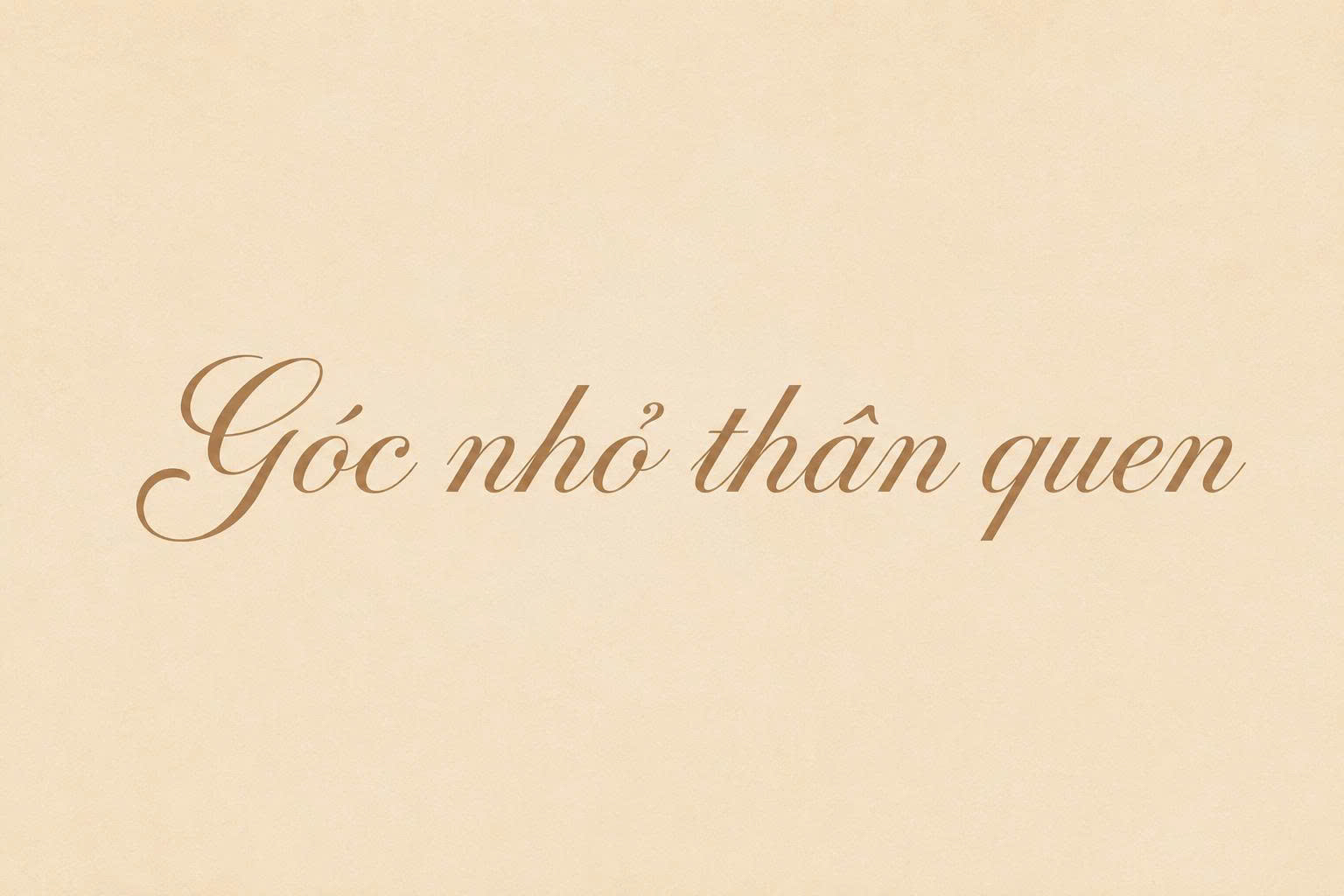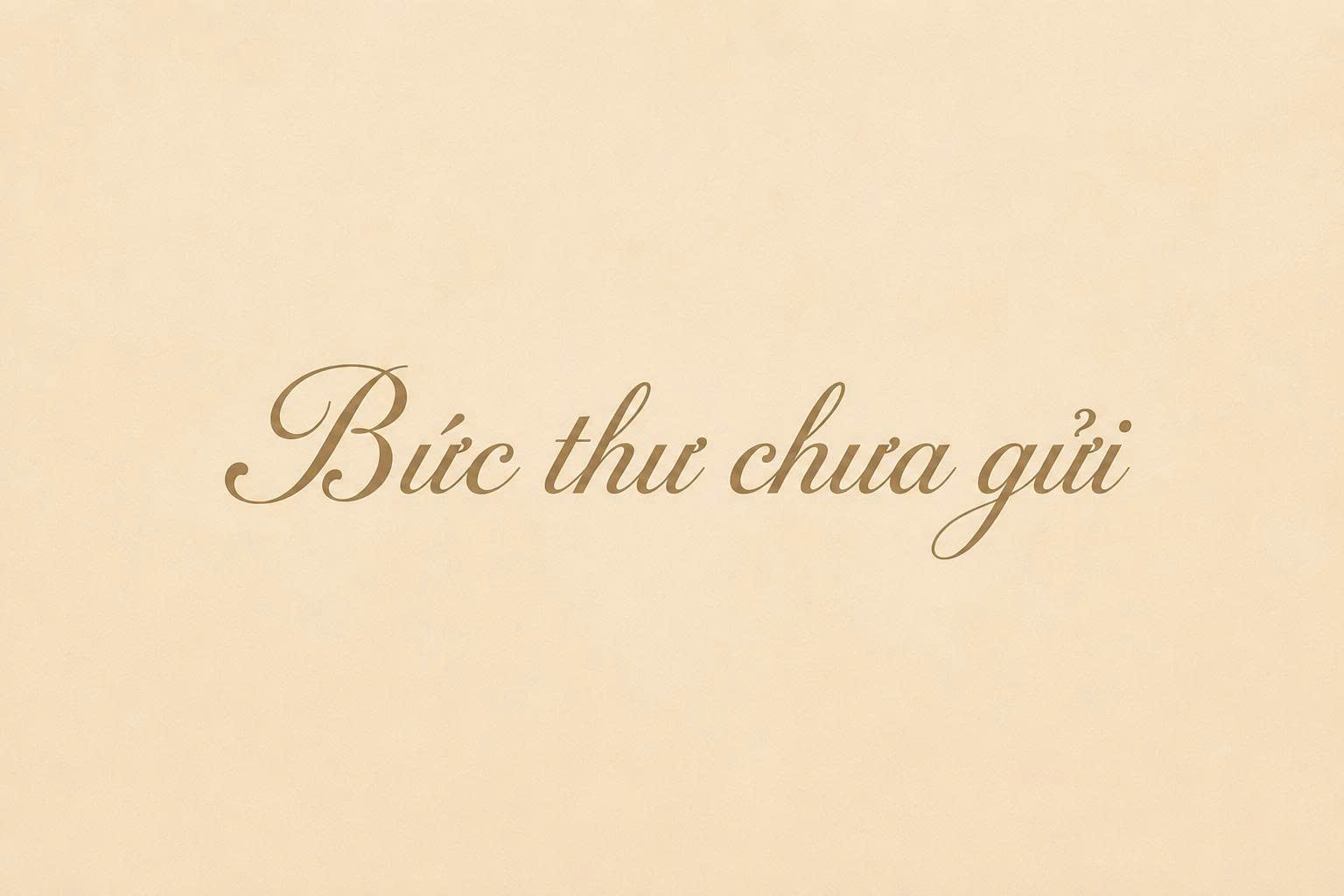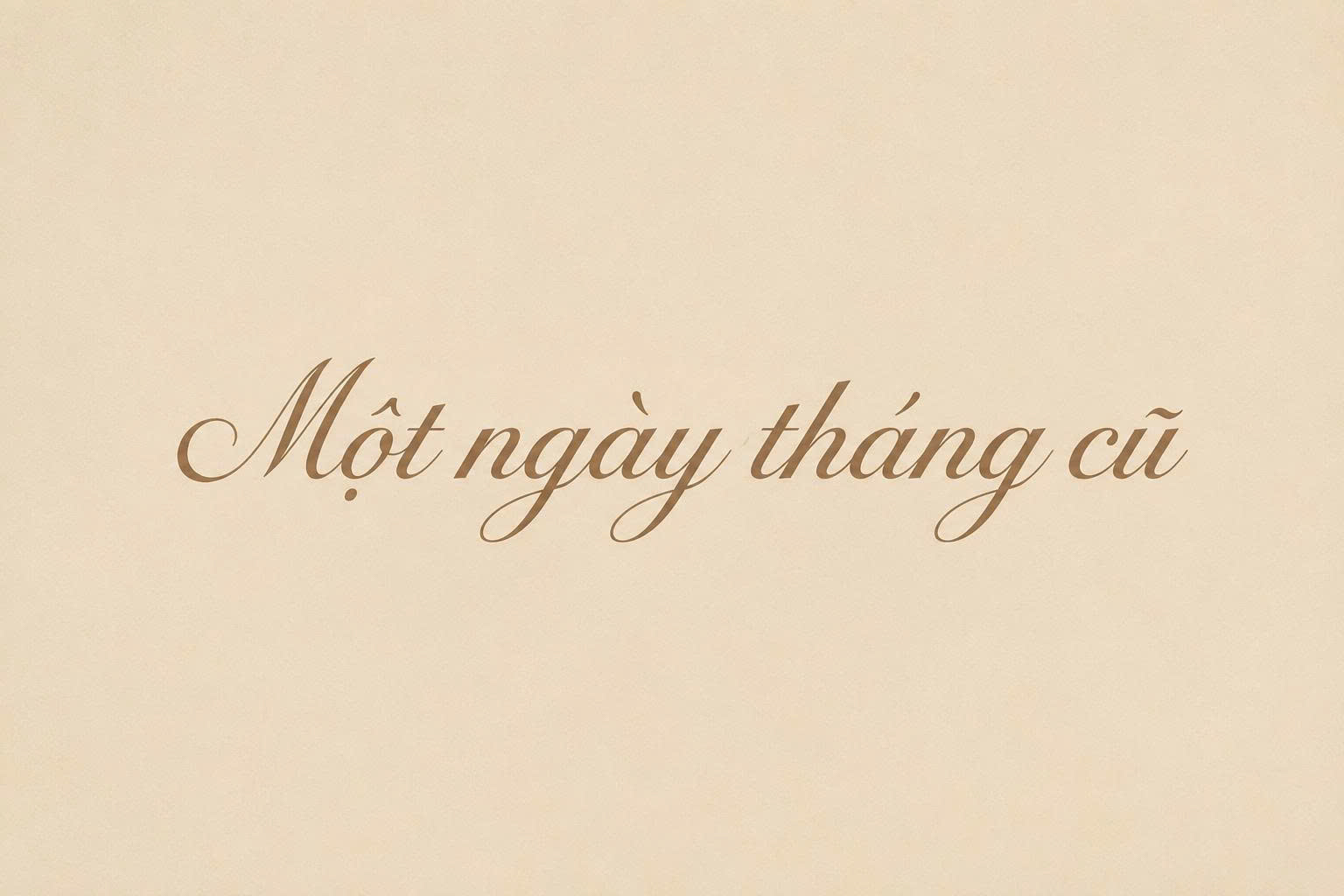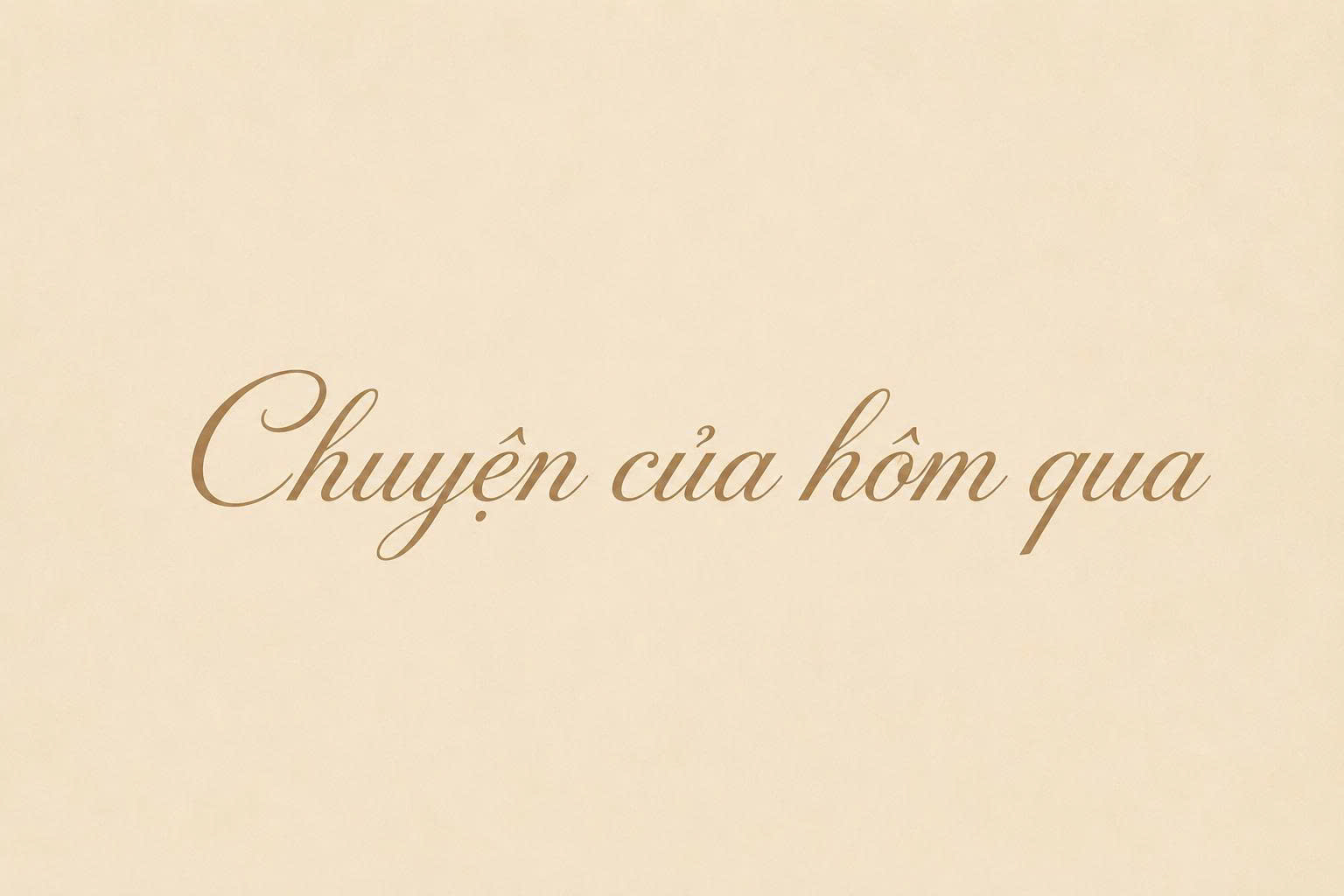
Font Việt hóa SVN Snell Roundhand Script là bộ phông chữ thư pháp (Calligraphy) cổ điển dựa trên lối viết tay của Charles Snell từ năm 1694. Với những đường nét uốn lượn tinh xảo, thanh mảnh và đầy quý tộc, đây là lựa chọn hàng đầu cho các thiết kế yêu cầu sự trang trọng tuyệt đối như thiệp mời, bao bì mỹ phẩm luxury hoặc các loại chứng chỉ cao cấp. Doozypack.vn chia sẻ link tải chuẩn giúp bạn sở hữu bộ font chữ tiếng Việt SVN-Snell Roundhand Script không lỗi dấu, đảm bảo tính thẩm mỹ cao nhất cho mọi bản thiết kế in ấn.
Đặc điểm thẩm mỹ của font chữ tiếng Việt SVN-Snell Roundhand Script
Snell Roundhand không chỉ là một phông chữ, nó là biểu tượng của sự thanh lịch vượt thời gian trong ngành đồ họa thế giới.
kiểu chữ thư pháp cổ điển với nét viết tay mềm mại
Vẻ đẹp cổ điển từ nghệ thuật viết thư pháp tay thế kỷ 17
Đặc trưng lớn nhất của font SVN Snell Roundhand Script là các đường nối chữ vô cùng mượt mà, mô phỏng lại áp lực đưa bút sắt đẫm mực trên giấy xuyến chỉ. Mỗi ký tự đều mang một nhịp điệu riêng, tạo nên tổng thể đoạn văn bản như một bức họa thư pháp thủ công, gợi nhắc đến những lá thư tay quý tộc thời xưa.
Cấu trúc chữ tròn trịa và độ tương phản nét thanh đậm cực lớn
Bộ font chữ tiếng Việt SVN-Snell Roundhand Script sở hữu sự tương phản rõ rệt giữa nét nhấn (nét đậm) và nét hất (nét thanh mảnh như sợi tóc). Cấu trúc chữ tròn trịa, đầy đặn giúp font chữ này giữ được sự mềm mại nhưng vẫn vô cùng uy nghi. Khi được Việt hóa, bộ dấu tiếng Việt được đặt ở vị trí tinh tế, không làm mất đi độ thoáng của các đường uốn lượn trang trí (swashes).
mẫu chữ calligraphy sang trọng cho thiệp và bao bì cao cấp
03 Lý do nên sử dụng font SVN Snell Roundhand Script Việt hóa cho bao bì cao cấp
Trong ngành sản xuất bao bì tại Doozypack.vn, Snell Roundhand luôn được các nhãn hàng cao cấp ưu tiên lựa chọn:
• Tạo dấu ấn Luxury: Font chữ này giúp sản phẩm ngay lập tức toát lên vẻ đắt tiền và đẳng cấp, phù hợp cho các dòng quà tặng doanh nhân.
• Xử lý nội dung tiếng Việt mượt mà: Bản Việt hóa giúp bạn gõ các tiêu đề như “Kỷ niệm ngày cưới” hay “Thương hiệu cao cấp” một cách trọn vẹn, không bị lỗi dấu thanh hay sai lệch khoảng cách chữ.
• Tính ứng dụng trường tồn: Dù qua nhiều thập kỷ, phong cách Roundhand vẫn luôn giữ vững vị thế trong các thiết kế đòi hỏi sự chuẩn mực và sang trọng.
03 Ứng dụng thực tế của font SVN Snell Roundhand Script tại Doozypack.vn
Nét chữ quý tộc của Snell Roundhand mang lại hiệu quả thị giác đặc biệt trên các ấn phẩm tại Doozypack.vn:
• Bao bì mỹ phẩm & Nước hoa: Dùng cho tên dòng sản phẩm hoặc các slogan ngắn trên vỏ hộp, tạo cảm giác sang trọng và tinh tế.
• Thiệp cưới & Thư tri ân: Là font chữ quốc dân cho các loại thiệp mời trang trọng nhất, thể hiện sự trân trọng đối với người nhận.
• Văn bằng & Chứng chỉ: Độ uy nghi của font chữ này rất phù hợp để in tên cá nhân trên các chứng nhận nghệ thuật hoặc bằng khen cao cấp.
thiết kế hộp mỹ phẩm sử dụng chữ viết tay thanh lịch
Lưu ý kỹ thuật từ xưởng in Doozypack khi in font nét mảnh
Việc sản xuất bao bì sử dụng font Snell Roundhand đòi hỏi designer cần lưu ý một số vấn đề tại xưởng in:
• Gia công ép kim (Hot Stamping): Các nét hairline của font có thể không bám kim nếu khuôn ép không được xử lý kỹ. Bạn nên tăng nhẹ độ dày nét chữ (Stroke) khoảng 0.05pt – 0.1pt nếu định gia công ép kim vàng hoặc bạc.
• Chọn chất liệu giấy: Font chữ này đẹp nhất khi in trên giấy mỹ thuật nhẵn mịn hoặc giấy Ivory cán màng mờ. Bề mặt giấy phẳng giúp các nét thanh không bị nhòe mực.
mẫu bao bì ép kim kết hợp kiểu chữ nghệ thuật cao cấp